Як замінити шрифт за замовчуванням в ms word - вектор розвитку
За замовчуванням, при створенні нового текстового документа в MS Word, в якості основного шрифту використовується Calibri висотою 11 пунктів. Кому як, а мені Calibri рішуче не подобається, особливо, при використанні його при оформленні серйозної документації. Старий добрий Times New Roman може бути і застарів морально, однак, для цієї мети підходить набагато краще.
Таймс виграє, ну правда!
Переключити шрифт, звичайно справа секундне, але коли доводиться багато працювати з текстом, ці секунди ... в загальному, починають здорово дратувати. На щастя, виправити ситуацію надзвичайно просто - MS Word дуже гнучкий в налаштуванні, і провести таку операцію, як заміна одного стандартного шрифту на інший, справа нікчемна. Якщо, звичайно, знати що робиш. Я знаю - а тим, хто не знає, зараз розповім і покажу, не менше докладно, ніж в прикладі про зміну стандартних розмірів полів в документі MS Word.
Замінюємо шрифт Calibri на Times New Roman в якості стандартного
Насамперед, створимо новий текстовий документ, можна навіть зовсім порожній. На вкладці «Головна» знайдіть групу «Шрифт». а в її правому нижньому кутку - маленьку кнопку-стрілку «шрифт» (втім, можете просто натиснути Ctrl + D на клавіатурі, ефект буде тим же).
Викликаємо вікно настройки шрифта в MS Word
У вікні «Шрифт» нас цікавить тільки перша вкладка. Зараз у вас напевно шрифтом за замовчуванням заданий безликий «+ Основний текст», а в якості розміру вказано число «11». Саме час змінити все на свій смак. Замість «основного тексту» встановлюємо улюблений Times New Roman (або будь-який інший шрифт), а розмір міняємо на більш звичний «12» (тим більше Times New Roman не такий великий як Calibri і з висотою 11 пунктів буде дрібнуватий).
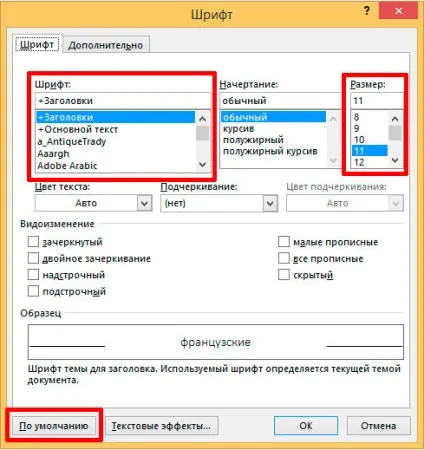
Міняємо шрифт основного тексту і застосовуємо зміни
Інші налаштування змінювати не бачу сенсу (навряд чи кого-то всерйоз цікавить можливість друкувати по-замовчуванню тільки великими і підкресленими буквами), тому натискаємо кнопку «За замовчуванням» в самому низу вікна. У який з'явився слідом вікні ставимо перемикач в нижнє положення ( «всіх документів заснованих на шаблоні Normal.dotm») і натискаємо «Ок».
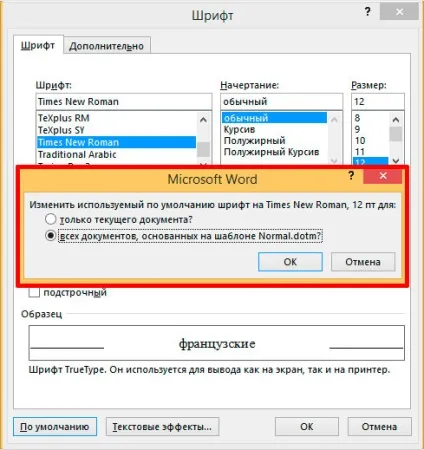
Не забудьте упевнитися, що зміни застосовуються до всього шаблоном документів, а не до поточного документа
Все готово - закриваємо MS Word (зберігати чи не зберігати документ - без різниці), після чого на екран швидше за все виведеться наступне вікно (якщо вікна немає - все в порядку, вам пощастило).
Пробуємо, запускаємо. Відмінно, шрифтом за замовчуванням дійсно став Times New Roman, з висотою рівною 12 пунктам.